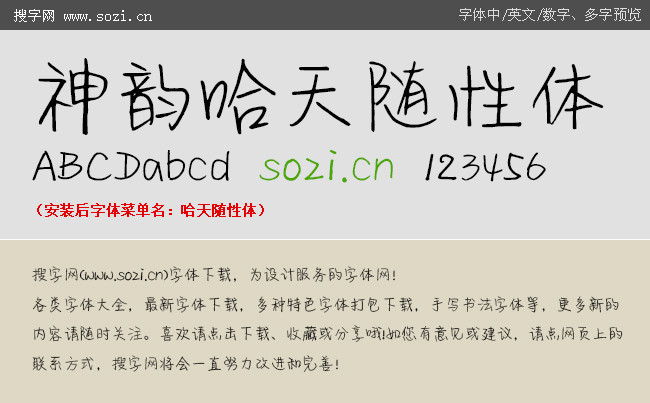
神韻哈天隨性體
搜字網(wǎng)給大家提供一款神韻哈天隨性體中文字體下載,神韻哈天隨性體一款十分美觀的手寫字體,字體流暢大方,整體效果非常出色,適合應(yīng)用于平面海報設(shè)計、包裝設(shè)計等廣告應(yīng)用。(本字體為個人非商用版,如需要商用請聯(lián)系作者購買版權(quán))